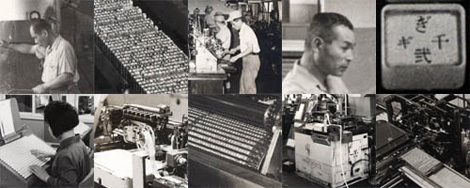
秀英体のコネタ
第7回 昭和30年代の職場見学
残されている昔の活版現場資料の中に、「スクラップブック 鋳植係職場写真 昭和30年代」と記された資料がありました。開いてみると、古い紙の匂いと何枚ものモノクロ写真が整理されて出てきました。
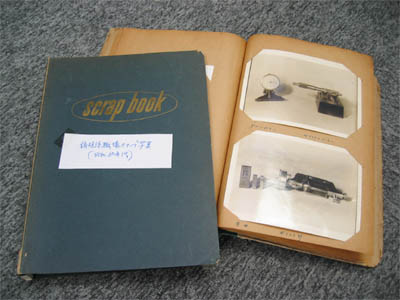
古いスクラップブック
何枚かの写真の裏には日付などとともに「職場優良賞受賞記念」と書いてありました。会社から賞をもらいその記念に撮影した職場写真のようです。今はもう残っていない古い印刷設備なども撮影されています。
昭和30年代の大日本印刷を見学してみましょう……。
いずれも今から40~50年ほど昔の写真です。
この写真の10年前である昭和20年代後半は、機械式母型父型彫刻機(ベントン彫刻機)の導入とそれにともなう新しい秀英体(A1書体・現在の秀英細明朝体)の開発がありました。そして写真の10年後の昭和40年代後半には、電算写植組版システムに搭載するため秀英体のデジタル化がスタートします。
昭和30年代は長い時間をかけて秀英体原字の修正を行なっています。創業以来使用してきた号数活字からポイント活字に完全に切り替わったのもこの時期です。もちろん新しい技術や設備の導入もあったでしょう。大日本印刷全体を見ても書籍や広告への印刷だけではなく、フォトマスク・家具に使う木目調シート・インスタントラーメンの包装材・布地への転写など、印刷技術から新しい製品を開発し、現在の総合印刷業へシフトしていくのが、この昭和30年代です。